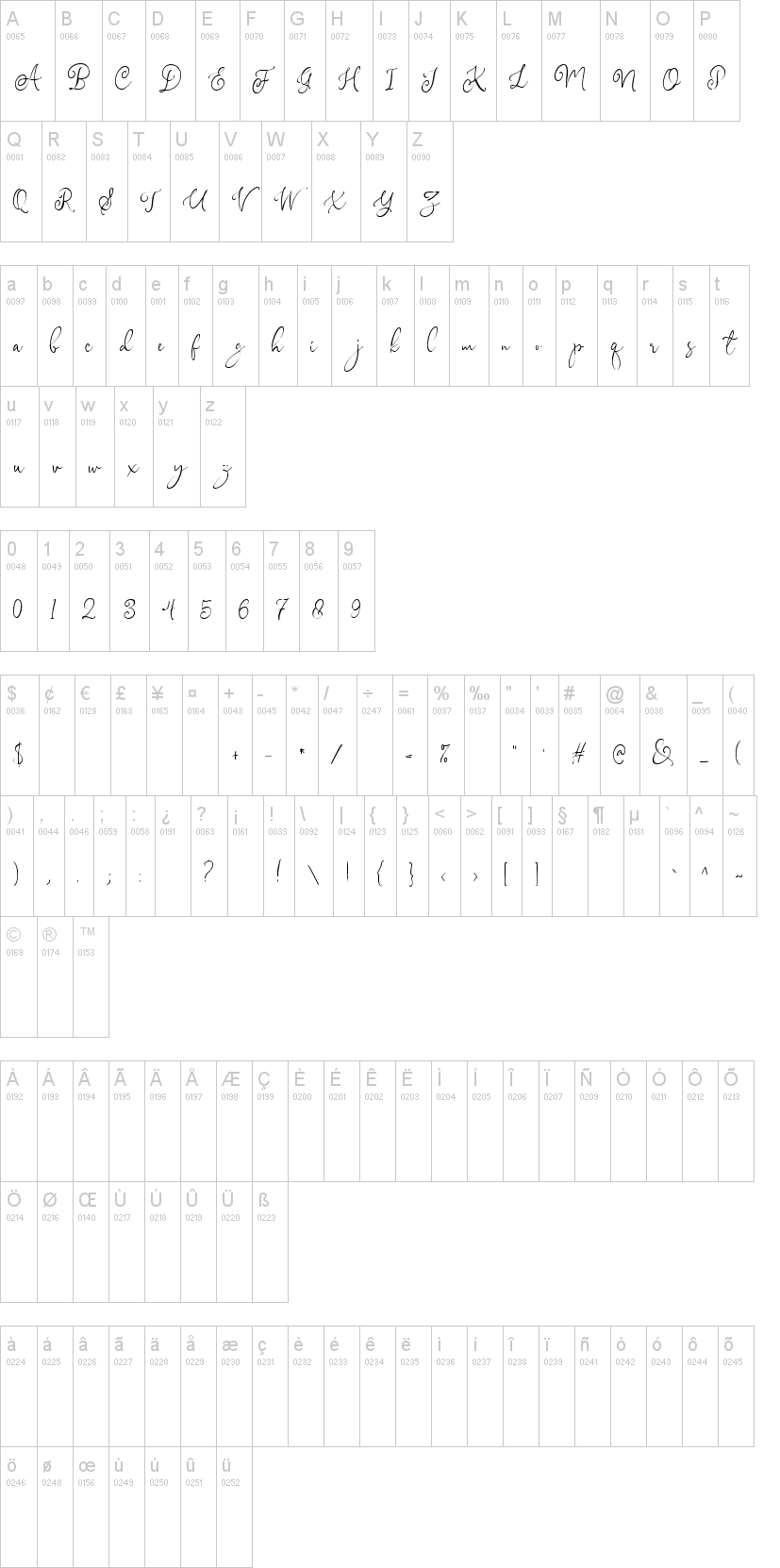
Gladiolus Script 是一种手写风格的字体,由 Font Bundles 开发并提供。它拥有优美的笔画和流畅的线条,在设计中可以带来自然和亲切的感觉。这种字体适用于各种场景,比如海报、名片、印刷品、包装设计等。它包含了多种字形和特殊字符,可以满足设计师的多样化需求。 Gladiolus Script 字体可以在 Font Bundles 上获得。内容介绍
Gladiolus Script是一款非常不错的手写艺术字体,具有很好的视觉感,适合于文化类的宣传设计、商业类品牌的广告和产品包装设计以及个性化文字排版等较多场景。